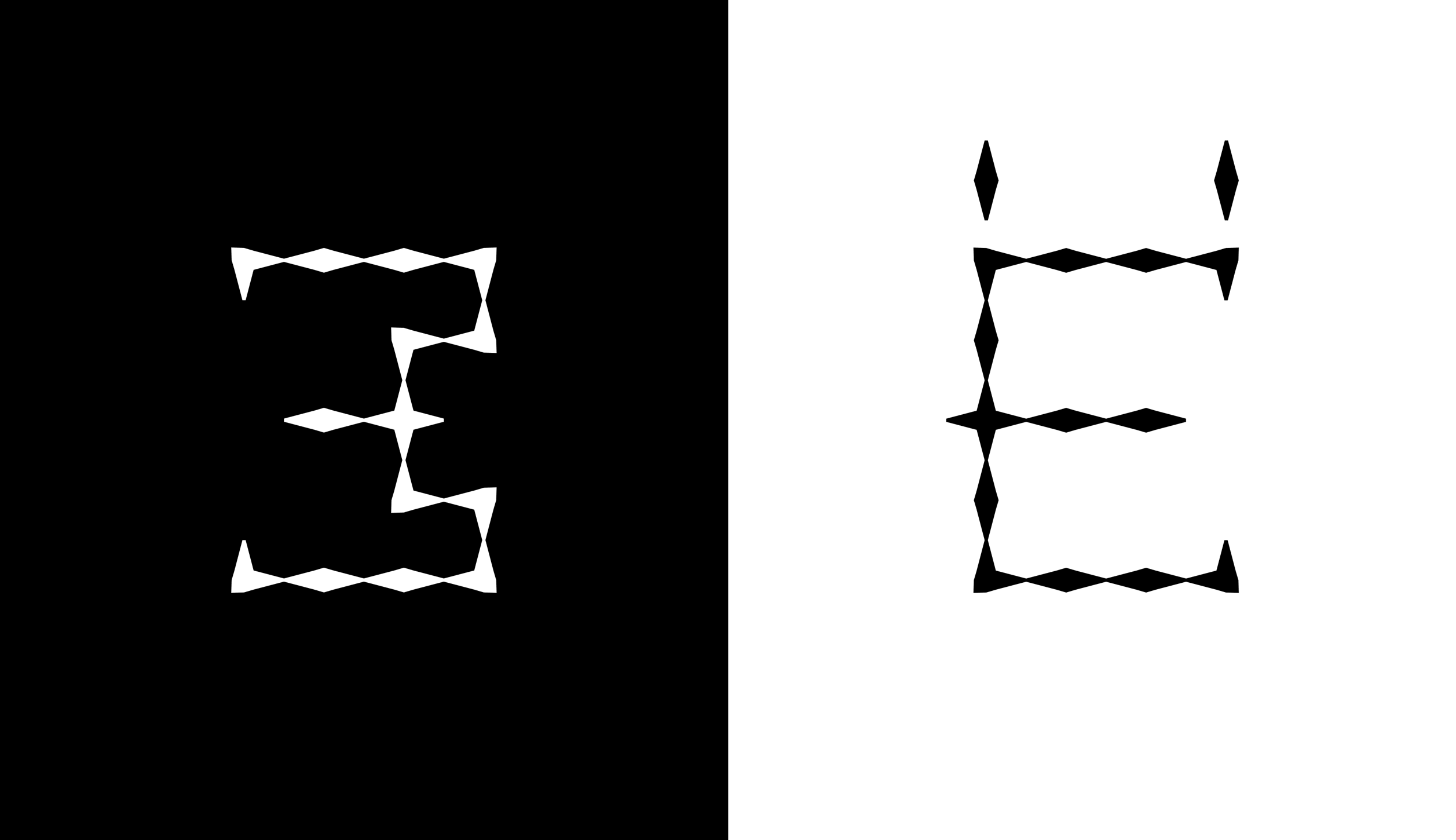
Шрифт Spear Serif
Spear Serif — это модульный шрифт, вдохновлённый наконечниками стрел и копий, сочетающий в себе промышленную гранёность и тонкое кованое изящество